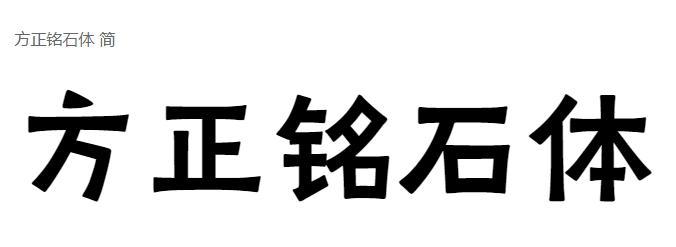
方正铭石体 简
方正铭石体,中国晋代墓志铭所用隶书被称为铭石体,典型例子为《王兴之墓志铭》,这种铭文的外形,也许在制作时增加了些许雕刻的细节,使其风格与现代的黑体字极为接近。
《王兴之墓志铭》全称《王兴之夫妇墓志铭》,是一块墓石,这块石头两面刻字,即分别刻夫妇两志。一面刻于东晋咸康六年(公元340年);另一面刻于永和四年(公元348年),碑文共计203字。
《王兴之墓志》书法封着端整,字体的介于隶楷之间,平整均匀,接近楷书,简化了隶书的一些波磔挑脚。中文部分为铭石体,西文部分为“K.E.Sagittarius”,方正铭石体是一款组合而成的综合书体。
方正铭石体